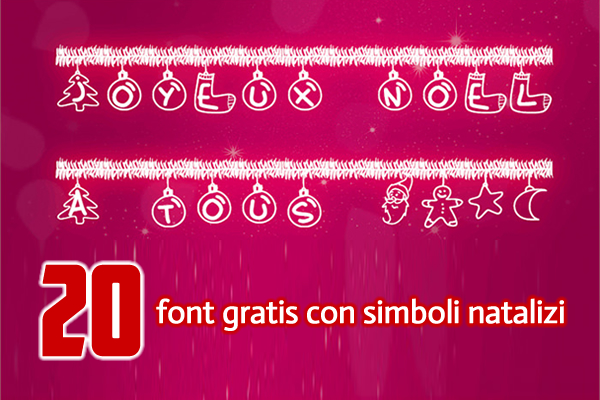
Se volete migliorare il vostro sito o i design per le festività natalizie, sicuramente avrete bisogno di alcuni font per trasmettere l'allegria natalizia.
A questo proposito, vi segnalo sul sito hongkiat una bella raccolta di font con simboli legati al Natale. Ci sono bastoncini di zucchero, cervi, fiocchi di neve e Babbo Natale tra questi caratteri simbolo.
20 font gratis con simboli natalizi